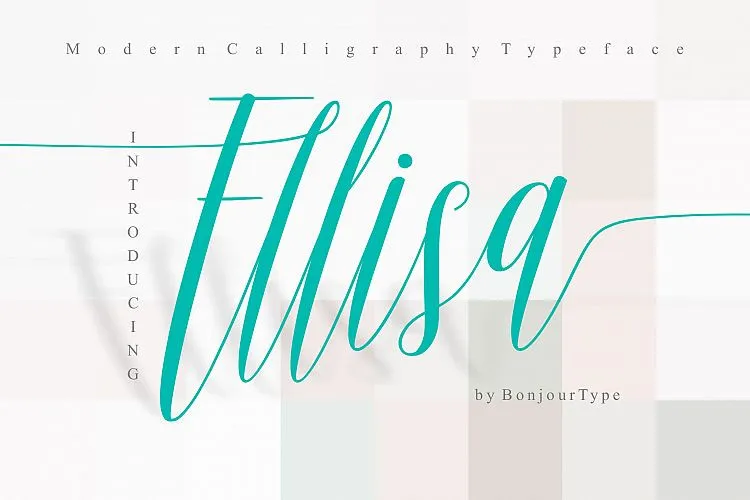
Ellisa Script Font – Download Grátis
Aqui está a descrição que você solicitou: O Elisa Script é uma fonte de estilo calligrafia casual e moderna, criada para aqueles que valorizam um toque personalizado na sua tipografia. Introduzida pelo designer 24Design, esta elegante fonte combina as influências da calligrafia tradicional com a contemporaneidade, resultando num conjunto único de caracteres. Ideal para uso em diversas aplicações gráficas, este Elisa Script é perfeito para assinaturas criativas, logotipos, cartas de casamento, etiquetas, materiais promocionais e até mesmo para design editorial. Suavizada por uma linha base em movimento que dança ao longo dos caracteres, a fonte oferece um toque moderno e refinado às suas criações. Seja você um designer gráfico profissional ou um amante casual da design, o Elisa Script é uma escolha perfeita para aqueles que procuram dar seu trabalho de design um toque único e personalizado. Com certeza vai deixar sua marca no mundo das comunicações visuais!